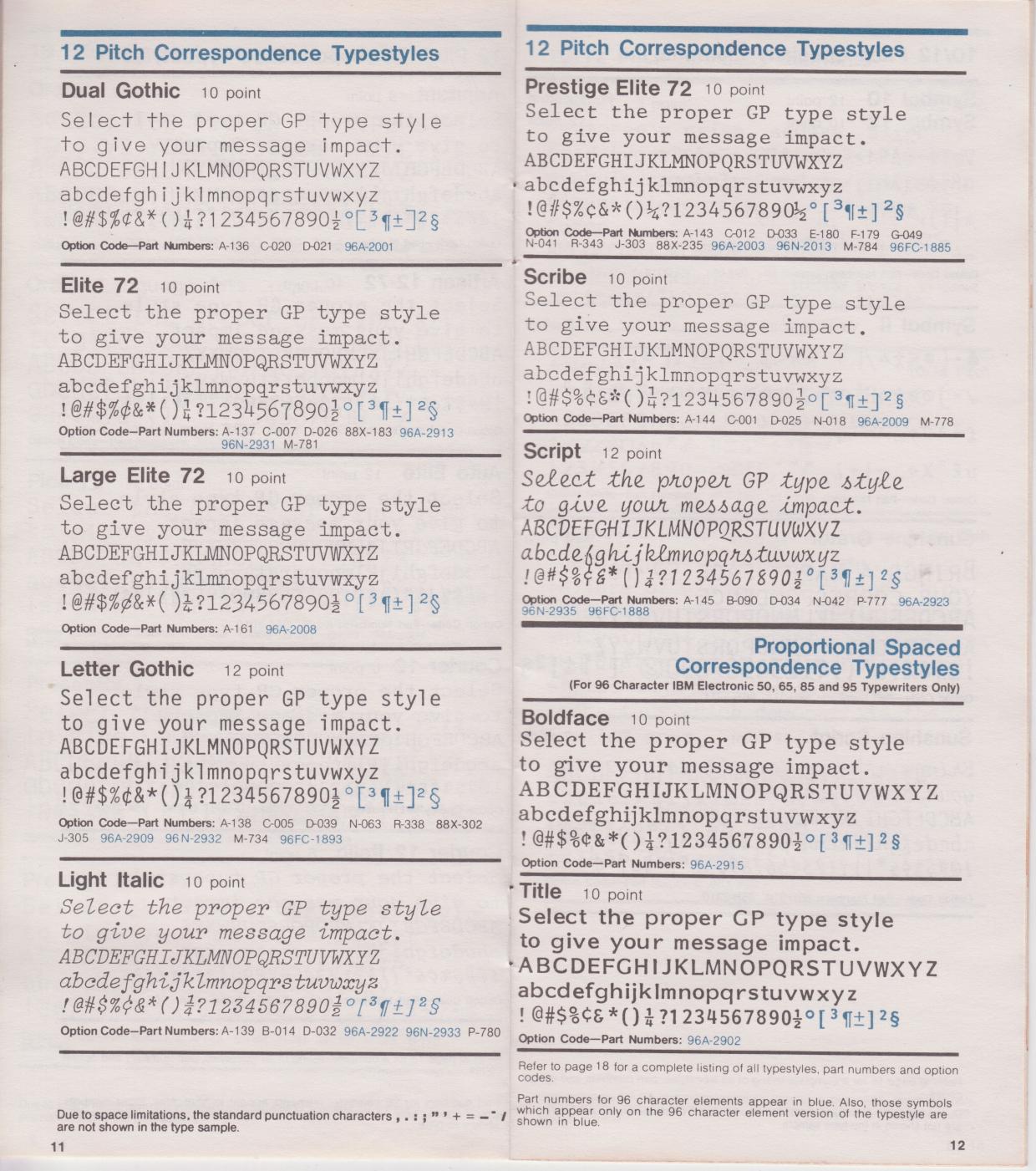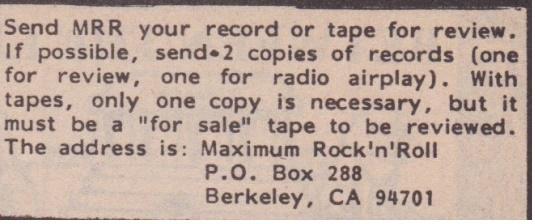
Wie heißt dieser sans Font aus dem Musikmagazin Maximum Rocknroll der 80er?
Dieser Font scheint eine alte Futura-Variation (40er/50er Jahre) zu sein. Markant für mich ist die offene vier. Recherchen bei whatthefont und anderen Seiten blieben leider ohne Ergebnis. Vielleicht erkennt jemand von euch diese Schriftart?
Dies Magazin heißt Maximum RocknRoll, kommt/kam aus den USA, (Printausgabe wurde dies Jahr eingestellt). Der Font war Fließtext und wurde so von 1982 bis 1989 verwendet. Dieser Scan ist von Ausgabe 44, Januar 1986.
Könnte ein Schreibmaschinenfont sein. Das Magazin wurde in bester Handarbeit zusammenkopiert …
Die "IBM Executive" und andere beherrschten Proportionalschrift, vielleicht ist hier was dabei: https://munk.org/typecast/2011/04/25/1964-nomda-blue-book-ibm-font-styles/
Der Font heißt schlicht und ergreifend Title 10 pt. und gab en natürlich (!) nur für einige ausgesuchte IBM-Schreibmaschinen. Artisan 12 kommt dem noch am nächsten. bertel, noch einmal vielen, vielen Dank für deinen Hinweis.
Hast Du einen Link auf weitere Informationen? Woher kennst Du diesen Font? Ich habe hier einiges rumliegen, auch die bereits verlinkte Seite mit den Beispielen:
Aber die Title 10 pt ist da nicht dabei? Woher hast Du diese Information? Aus der Redaktion des Magazins?
Diesen Font hätte ich natürlich gern. Allerdings gab es  den ja nur für ausgesuchte IBM-Schreibmaschinenmodelle. Artisan 12 kommt dem aber schon recht nahe.
Tausend Dank! Das hat mir in der Dokumentation gefehlt. Ich würde diese Schrift aber nicht der Futura zuschlagen. Das geht eher in die Richtung einiger andere Groteskschriften aus den 1920er.
Ja, das sehe ich mittlerweile auch so. Nur hatte ich bis dato keinen anderen Vergleich.